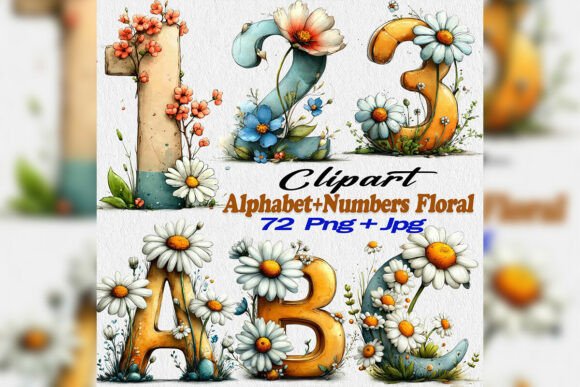
Watercolor Floral Alphabet and Letters
Het vinden van de juiste ontwerpelementen kan lastig zijn, maar Watercolor Floral Alphabet and Letters biedt een uitzonderlijke collectie die uw werk direct naar een hoger niveau tilt.
Of u nu POD-producten (Print on Demand), huwelijksuitnodigingen of afbeeldingen voor sociale media maakt, Watercolor Floral Alphabet and Letters is een ideale keuze.